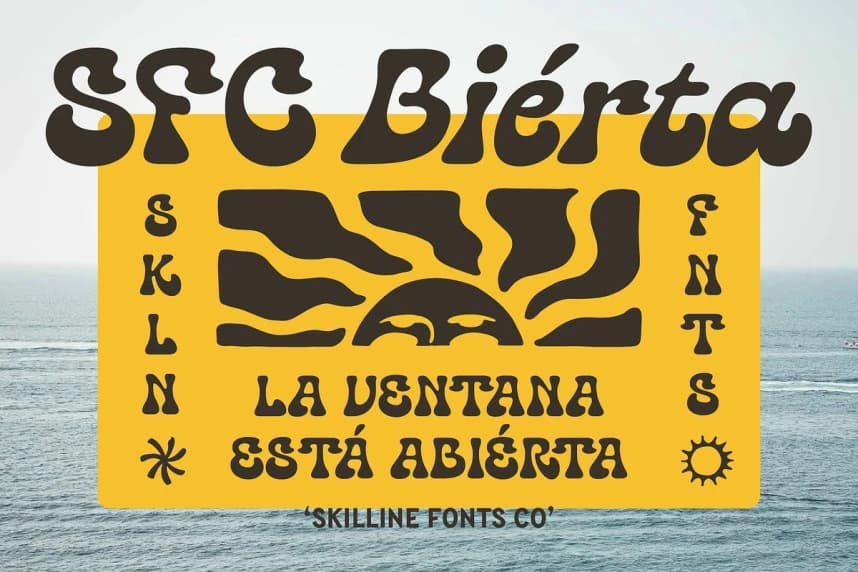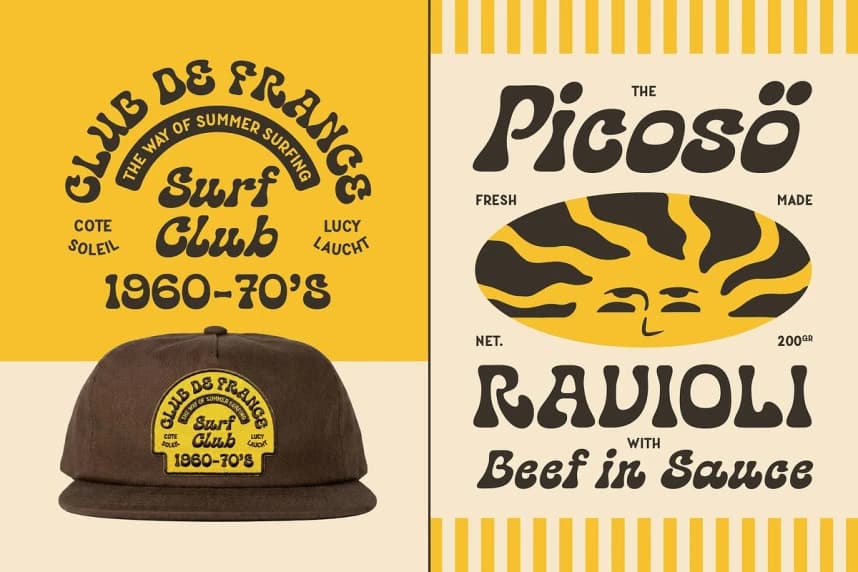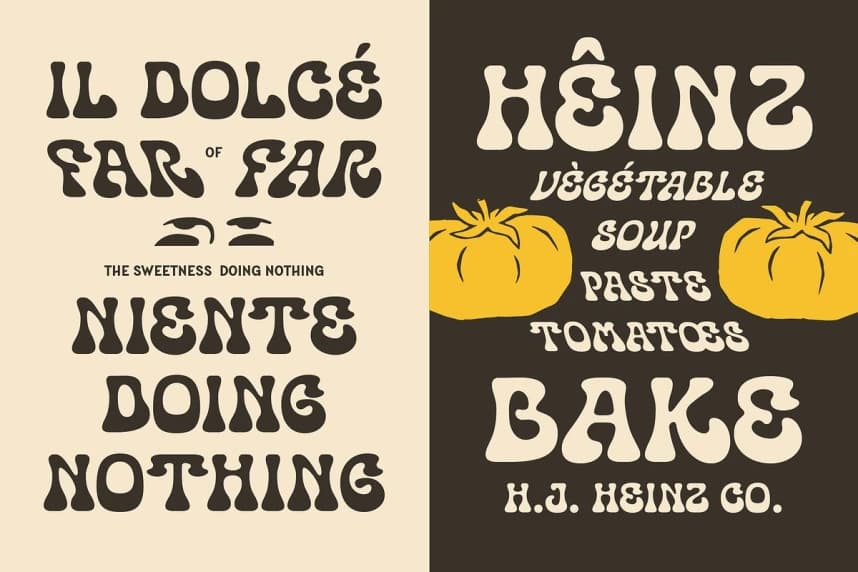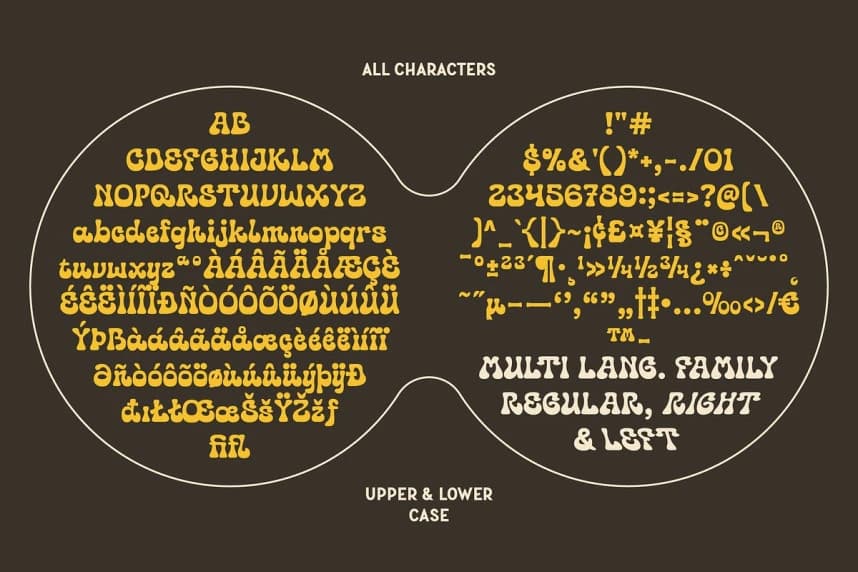
SFC Biérta Font
SFC Bierta Font, 60’lar–70’ler’in psikedelik tipografisinden, sörf kültürü grafikleri ve vintage gıda ambalajı estetiğinden ilham alan cesur bir retro gösteri yazı tipidir. Kalın eğriler, yumuşak organik kenarlar ve oyunbaz oranlarla tasarlandı; Bierta, funky ve sıcak bir hava sunar.
SFC Bierta Font, 60'lar–70'ler psikedelik tipografisinden, sörf kültürü grafikleri ve vintage yiyecek ambalajı estetiğinden esinlenen cesur bir retro gösterim yazı tipidir. Kalın eğriler, yumuşak organik kenarlar ve oyuncu oranlarla tasarlanmıştır; Bierta eğlenceli ve sıcak bir hava sunar.